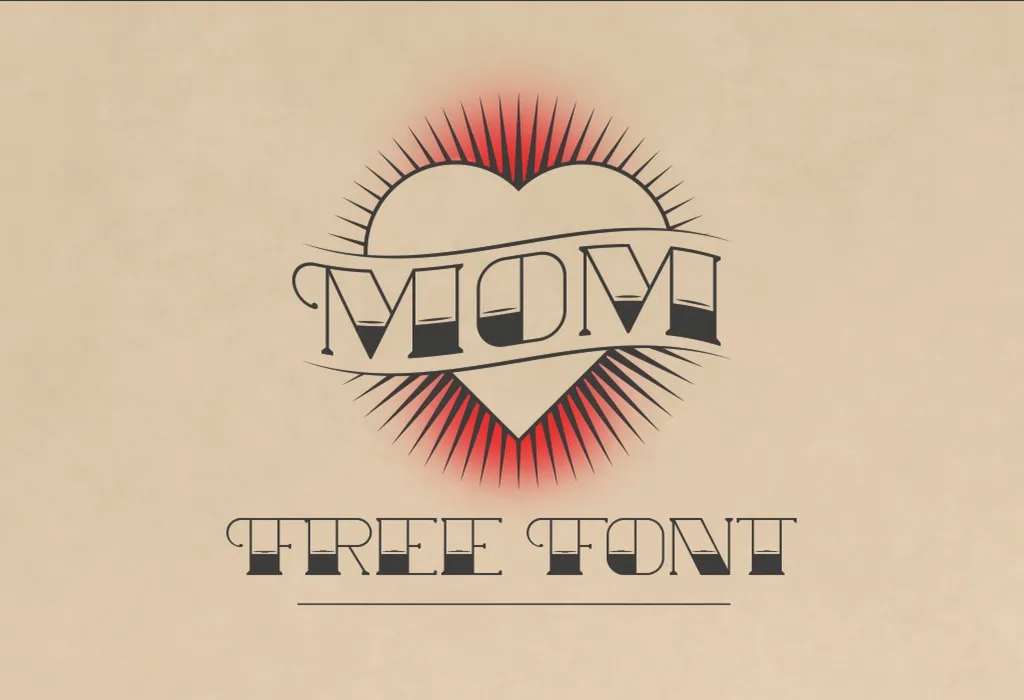
A fonte “Mom Font Family” é ideal para decorar ambientes, dando um toque divertido e único a seus projetos. Criada por Hamilton, essa família de fontes se destaca com traços fluidos e cores vibrantes que prometem enriquecer qualquer layout. Seja para criar cartazes, tags personalizadas ou até mesmo decorações da casa, você encontrará em “Mom Font Family” os recursos necessários para manter seu design sempre original. Com uma ampla gama de opções entre as diferentes fontes que compõem esta família, é fácil encontrar a perfeita para atender às suas demandas específicas. Sua versão Decorative certamente será o elemento diferenciador que lhe dará aquele toque especial ao qual você sempre almejou em seu trabalho visual.